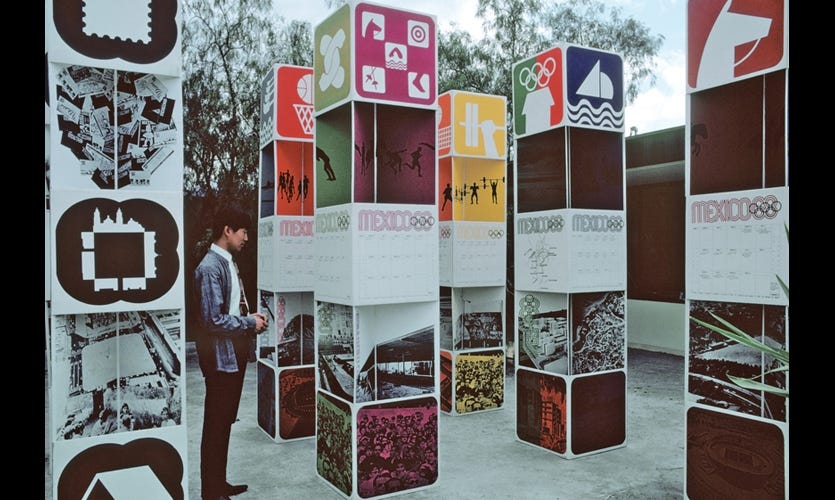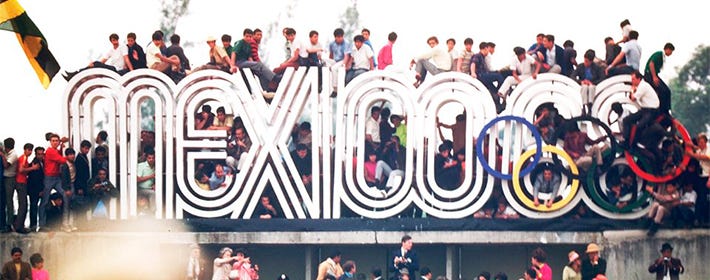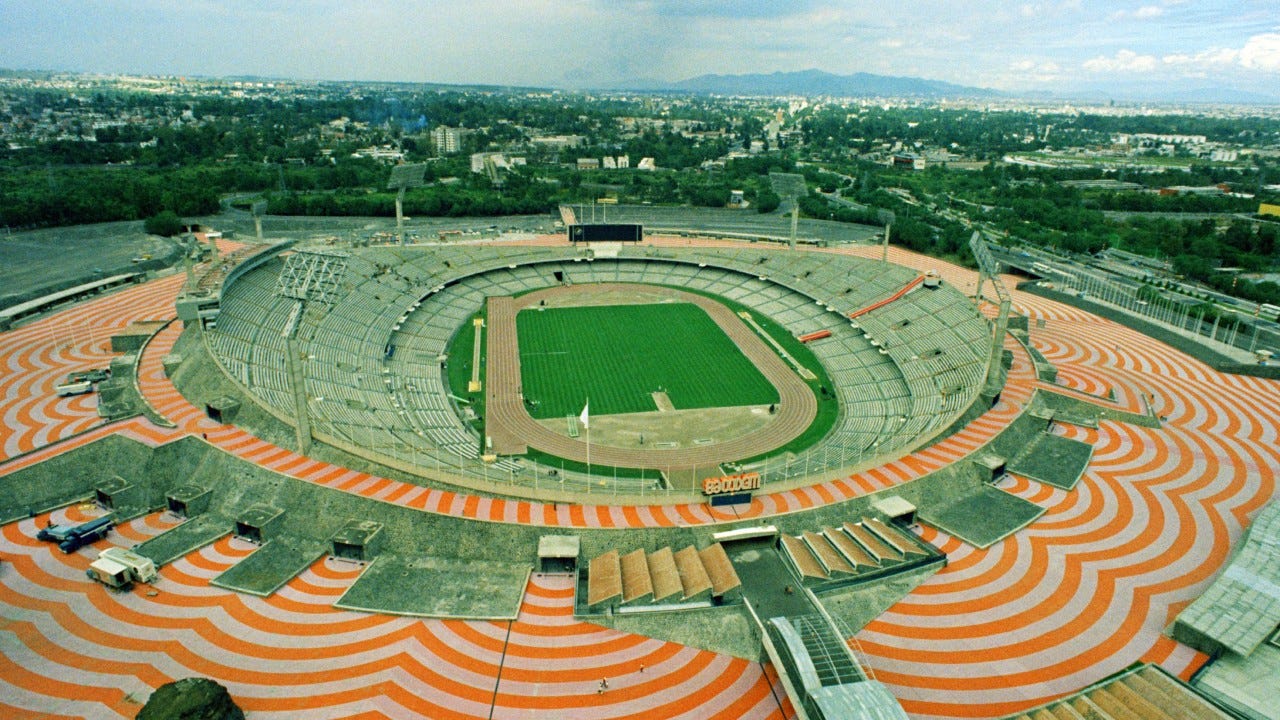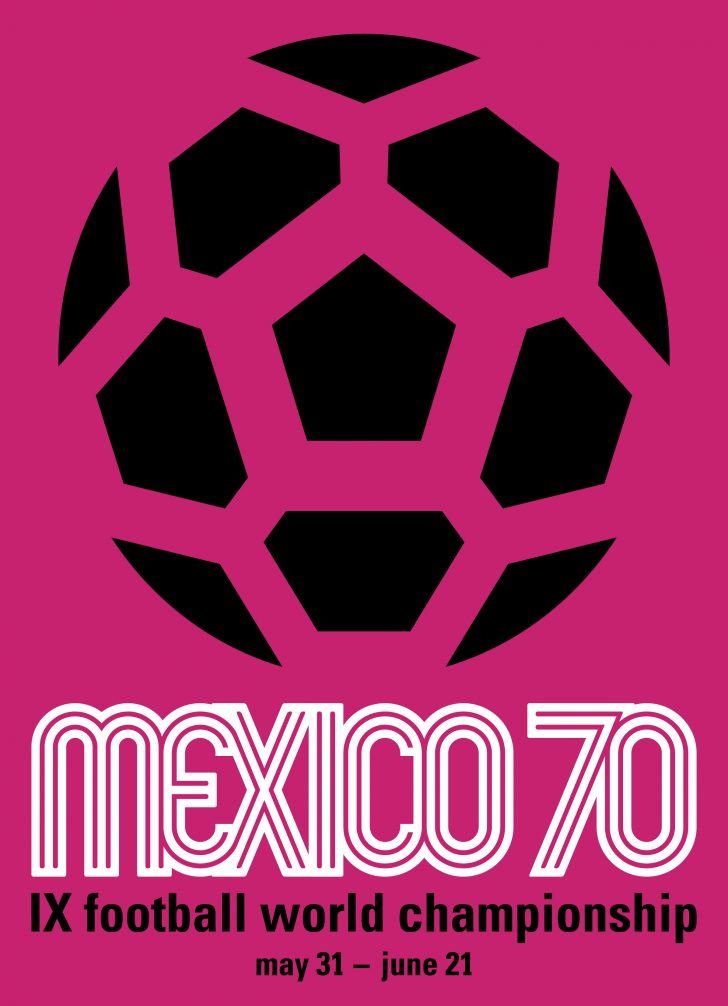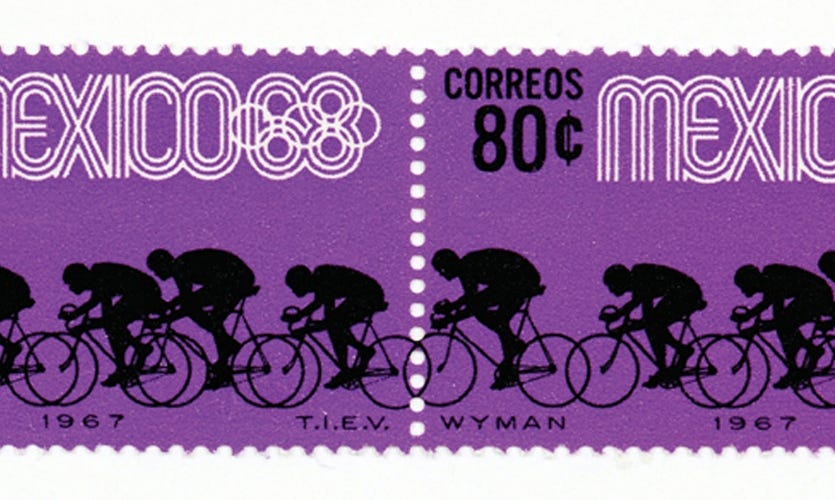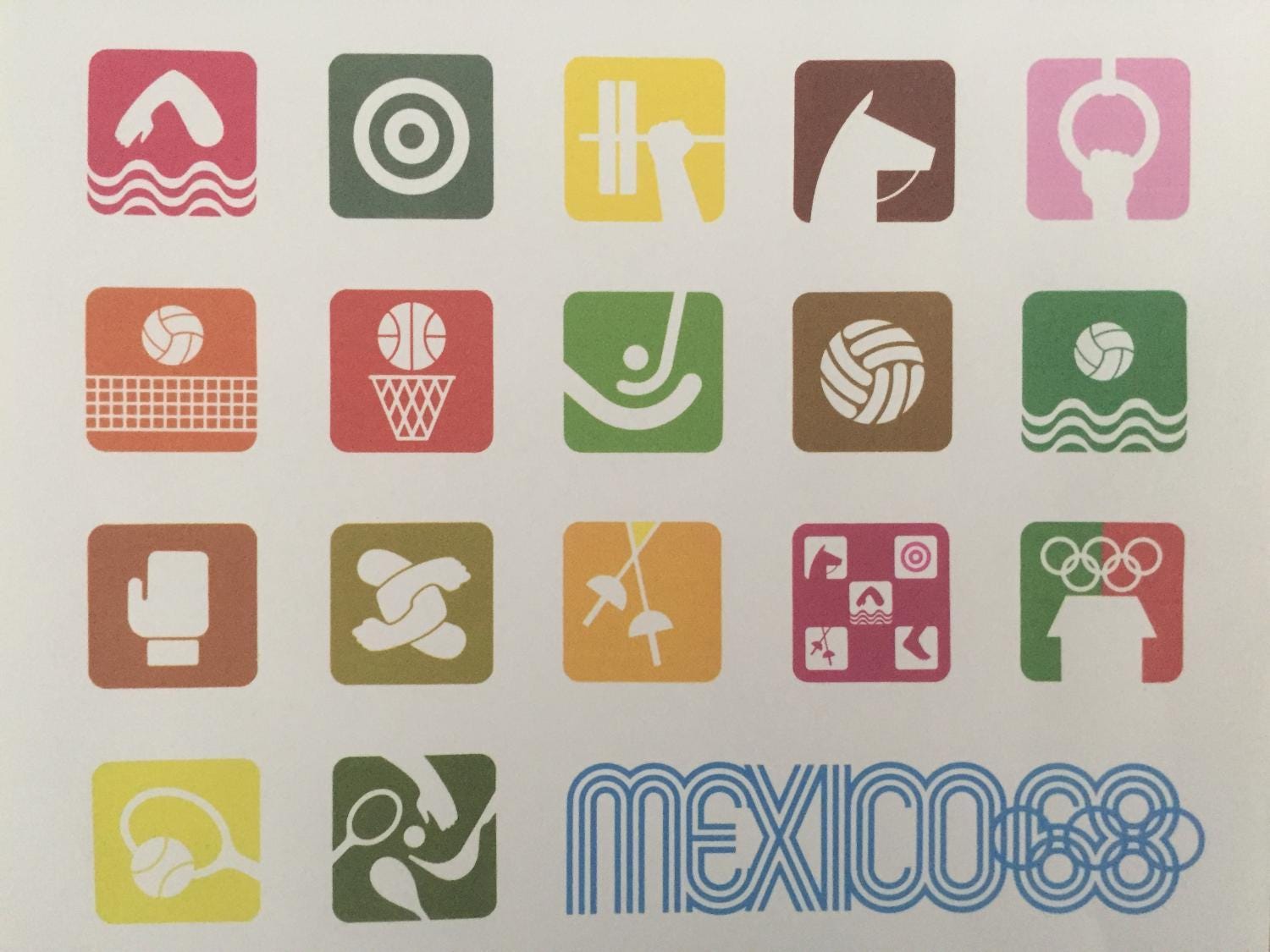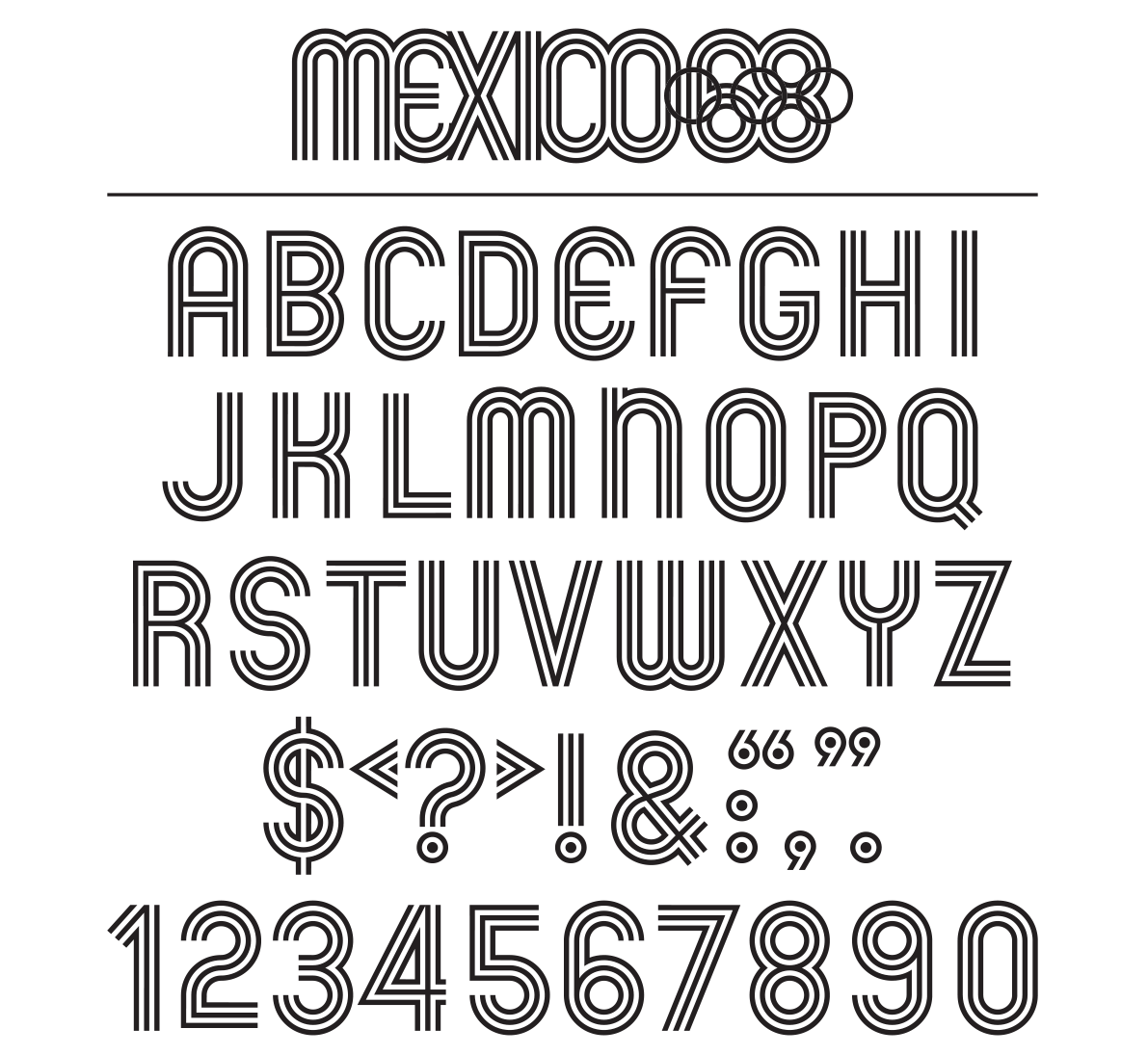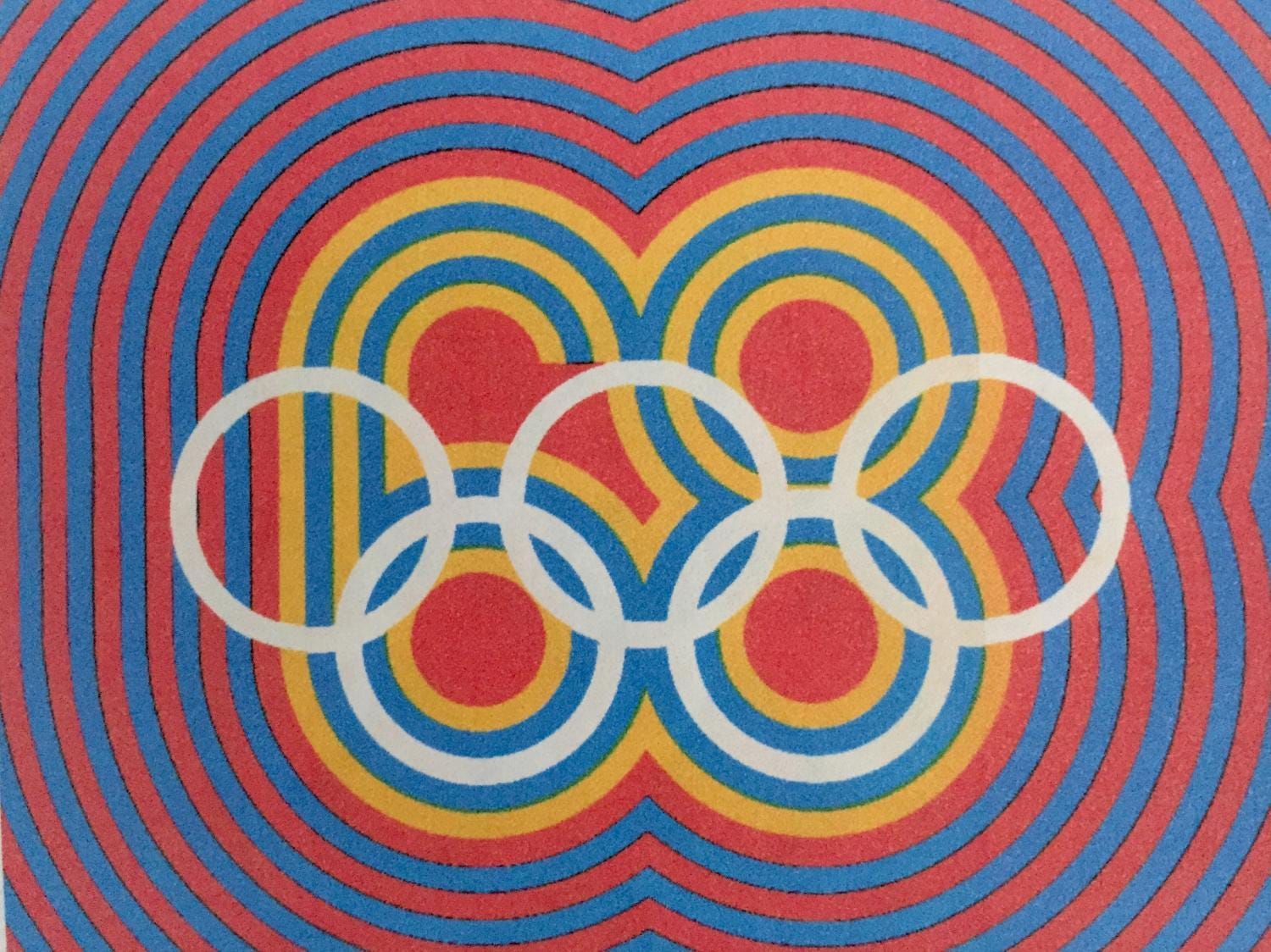
Até hoje, só quatro países ousaram receber edições seguidas de Copa do Mundo e Olimpíadas. Como você pode imaginar, organizar os dois maiores eventos esportivos do mundo num espaço de tempo tão curto e lidar com duas organizações esportivas que se odeiam exige grandes doses de paciência e uma economia capaz de suportar os investimentos em infra-estrutura esportiva. A Alemanha sediou as Olimpíadas de Verão de 1972 em Munique e a Copa do Mundo de 1974, sendo campeã em casa e fazendo dessa dobradinha de eventos uma vitrine da capitalista Alemanha Ocidental. Em 1994, os Estados Unidos receberam a Copa do Mundo do tetracampeonato brasileiro e, em 1996, as Olimpíadas de Verão em Atlanta, Geórgia. O Brasil também entra nessa estatística, recebendo um 7 a 1 a Copa em 2014 e as Olimpíadas de Verão em 2016 após uma década de crescimento econômico e o início de uma convulsão social que dura até hoje.
Contudo, nesses três casos, houve uma preocupação em estabelecer identidades visuais distintas para cada evento. O único caso em que uma mesma marca foi usada nas Olimpíadas de Verão e na Copa do Mundo foi no México, em 1968 e 1970. A célebre marca é um ícone do design gráfico, ostentando até hoje a importância que teve para o esporte e a cultura mundial. Falar dessa marca evoca também uma história de disputa de autoria, convulsão social e momentos icônicos do esporte. Então, já que estamos em clima de Copa do Mundo, o Tipo Aquilo de hoje aborda um pouco da história do logotipo que deu cara e tom às Olimpíadas de Verão da Cidade do México de 1968 e à Copa do Mundo de 1970.
A princípio, as jornadas de 2013 parecem uma certa repetição do Movimento Estudantil de 1968 no México: pessoas indo às ruas protestar contra um governo moralmente questionável que esbanjava dinheiro em obras para grandes eventos. Para o bem dos menos atentos, as semelhanças acabam aí. No México de 1968, o buraco era mais profundo: desde 1929 o país vivia com o PRI (Partido Revolucionário Institucional) ininterruptamente no poder. A exemplo de vários países da América Latina, o México tornava-se mais autoritário, sob influência da política anticomunista dos EUA, vivendo entre as décadas de 1960 a 1980 as chamadas Guerras Sucias: com o pretexto de deter o narcotráfico, as forças militares mexicanas agiram com força contra grupos guerrilheiros e movimentos de esquerda, incluindo prisões arbitrárias e execuções sumárias.
Contudo, o país vivia um franco crescimento econômico desde os anos 1940, em que a estabilidade política oferecida pelo PRI, investimentos maciços em urbanização e industrialização do México e absorção de unidades fabris de empresas americanas levaram ao chamado “milagre mexicano” (é, crianças, nada se cria), que ajudou a desenvolver a economia mexicana, mas ampliou a desigualdade entre as áreas rurais e os centros urbanos. Como vitrine de um modelo econômico que ostentava um crescimento médio de 4% ao ano, no início da década de 1960, o governo mexicano postulou suas candidaturas aos maiores eventos esportivos. Em 1963, a candidatura da Cidade do México venceu Detroit, Lyon e Buenos Aires; no ano seguinte, os mexicanos derrotaram mais uma candidatura argentina, dessa vez na FIFA.
Ante o desafio de mostrar o país como uma economia sólida e uma população vibrante e unida em prol das Olimpíadas, o arquiteto Pedro Ramírez Vásquez foi escolhido como presidente do comitê organizador dos Jogos Olímpicos. Vásquez tinha em seu portfolio o Estadio Azteca e o Museu Nacional de Antropologia da Cidade do México; para desenvolver o sistema de design gráfico e identidade visual dos jogos, tinha ao seu lado os arquitetos Eduardo Terrazas e Manuel Villazón, e a designer inglesa Beatrice Trueblood, que havia trabalhado com Ramírez editando publicações do Museu de Antropologia. Junto a estes, somaram-se os designers e sócios Peter Murdoch e Lance Wyman, uma estrela ascendente que havia trabalhando na divulgação dos EUA projetando pavilhões do país em exposições internacionais, e que conseguiu a confiança de Terrazas e Trueblood.
Wyman, pouco letrado sobre a cultura mexicana, ambientou-se rapidamente no país e, junto com a equipe, ajudou a desenvolver o sistema de identidade visual de eventos esportivos mais robusto até então. O desafio de conceber um símbolo que projetasse a história, cultura e identidade mexicana para o mundo encontrou uma resposta singela em um dos vários rabiscos de Vásquez, segundo Beatrice. Um desses rascunhos trazia os números 6 e 8 com suas contra-formas formando dois dos três anéis olímpicos, e logo o rascunho tornou-se um dos emblemas mais memoráveis da história do esporte. A feliz coincidência entre os anéis olímpicos e as formas redondas dos números foi transformada em uma marca que, sob o espírito de seu tempo, conjugava a geometria, a op art, a arte mexicana pré-hispânica e os padrões visuais dos Huichol em um sistema vibrante e colorido, que afastava o país de estereótipos e inseria-o numa cultura visual moderna com um logotipo memorável.
Enquanto os pictogramas tinham um papel fundamental nas Olimpíadas de Verão de Tokyo, em 1964, de auxiliar na comunicação e localização de atletas, voluntários, comissários e o público internacional num país com língua e escrita próprias, a equipe de Ramírez deu um passo além, reinterpretando-os de acordo com a cultura mexicana e dando destaque aos artefatos e partes do corpo mais proeminentes de cada esporte. Wyman encontrou terreno fértil na programação visual dos Jogos Olímpicos para projetar pictogramas, selos, vestuário, wayfinding e dezenas de outras aplicações que tornaram-no célebre o suficiente para ser confundido, por várias vezes, como autor da marca. Além das Olimpíadas, Wyman fez diversos trabalhos como designer no México, destacando-se a identidade visual e sistema de wayfinding do Metrô da Cidade do México.
O trabalho brilhante de Wyman, Ramírez, Trueblood e os demais designers e arquitetos resultou numa identidade visual celebrada até hoje, sendo uma das grandes memórias dos Jogos Olímpicos. Somam-se a essa memória a primeira transmissão ao vivo em cores das Olimpíadas; a tocha olímpica refazendo o caminho de Colombo até a descoberta da América; os punhos em riste dos atletas afro-americanos Tommie Smith e John Carlos em protesto pela discriminação racial nos EUA; a cabeça baixa da ginasta Věra Čáslavská em protesto contra a invasão da Tchecoslováquia pela União Soviética; e o triste episódio do massacre de Tlatelolco, em que de 300 a 400 manifestantes foram executados pelo governo e mais de mil pessoas foram presas, ocorrido a apenas dez dias da abertura dos Jogos Olímpicos, até então promovidos como “Los juegos de la Paz”.
Para a Copa do Mundo de Futebol, a Fifa passou a assumir a criação das identidades visuais de seus eventos a partir de 1970. A primeira transmissão global do evento também teve um novo elemento de destaque: a Telstar. A bola projetada pela Adidas, maior símbolo do futebol até hoje, trouxe como novidade o uso das cores preto e branco, que tornava a bola facilmente identificável em transmissões em cinza, comparada com as bolas marrons das copas anteriores. Como uma homenagem ao trabalho de design criado para os Jogos Olímpicos de 68, a Copa do Mundo em que o Brasil sagrou-se tricampeão e dono definitivo da taça Jules Rimet trouxe como identidade visual uma simplificação do desenho da Telstar junto com o logotipo dos Jogos Olímpicos adaptado para o ano de 1970, sendo a única vez em que um único símbolo foi usado nos dois eventos.
A Copa do Mundo de 1970 trouxe outras novidades, como a substituição de jogadores, os cartões amarelo e vermelho e os álbuns licenciados de figurinhas de jogadores. O México recebeu mais uma Copa do Mundo em 1986 (no lugar da Colômbia), tendo sua identidade visual pouco lembrada em relação à sua antecessora, e receberá o evento novamente em 2026, junto com EUA e Canadá. O Estadio Azteca, palco do jogo final e criação de Ramírez Vásquez, tornou-se um templo do futebol, e o trabalho de sua equipe ajudou a definir uma identidade visual para o esporte, como um todo, com o uso de linhas paralelas tornando-se um clichê para representar competições e esportividade. Embora a realização dos jogos de 1968 tenham custado a vida de centenas de estudantes, a força que o símbolo dos Jogos Olímpicos de 1968 tem, ao afastar-se dos estereótipos e lugares comuns sobre a história do México, faz com que ele marque o momento do país e seja reverenciado e revisitado até hoje.